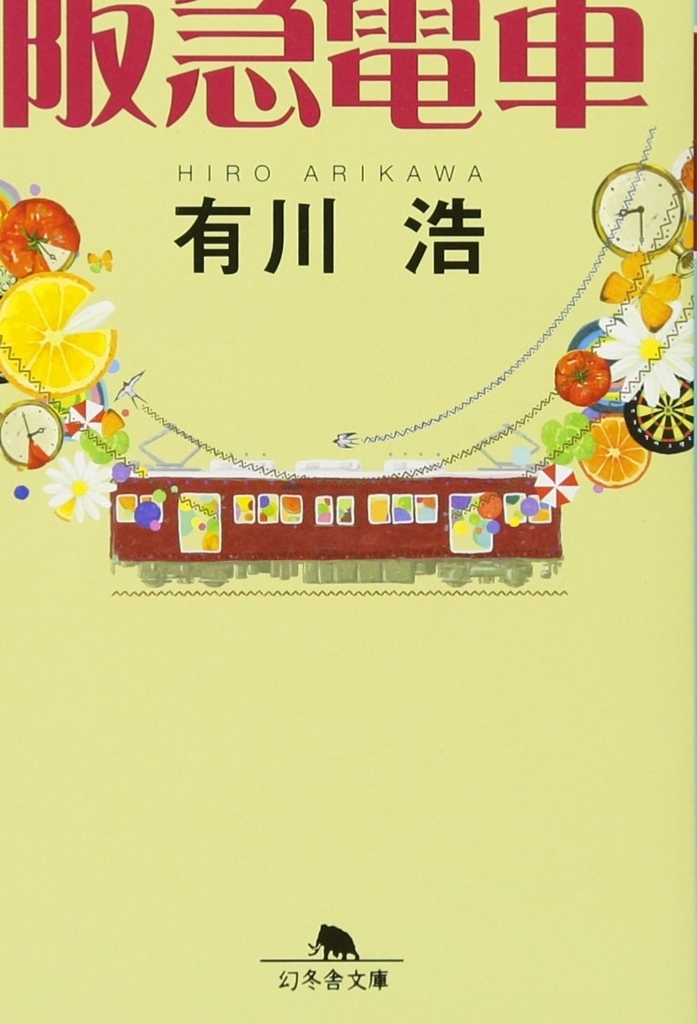
阪急電車
阪急電車 片道15分の奇跡
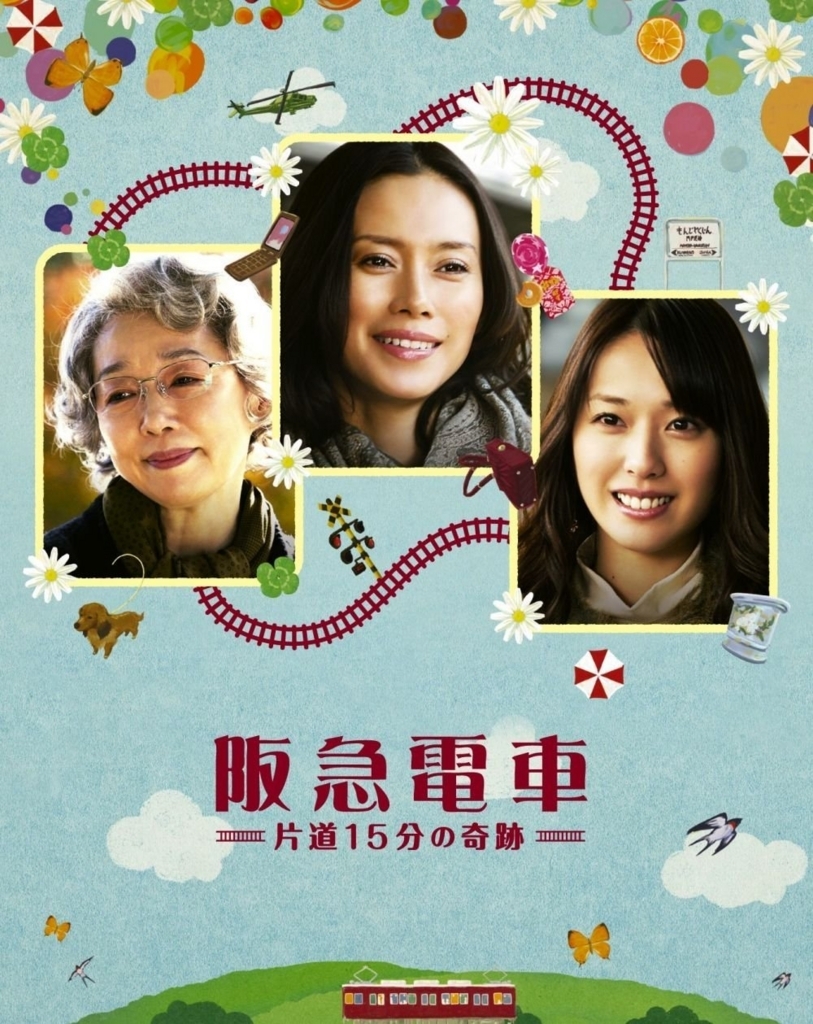
書籍「阪急電車」、映画版「阪急電車 片道15分の奇跡」のタイトルにダイナフォントの麗雅宋が採用
書籍の「阪急電車」、映画版の「阪急電車 片道15分の奇跡」のタイトルにダイナフォントの麗雅宋が採用されている。
麗雅宋
明朝体のストロークをベースに特徴的なカーブがかったエッセンスが加わり、どことなく南国の雰囲気に溢れた書体。麗雅宋の和文用仮名は「有限会社 字游工房」が制作している。